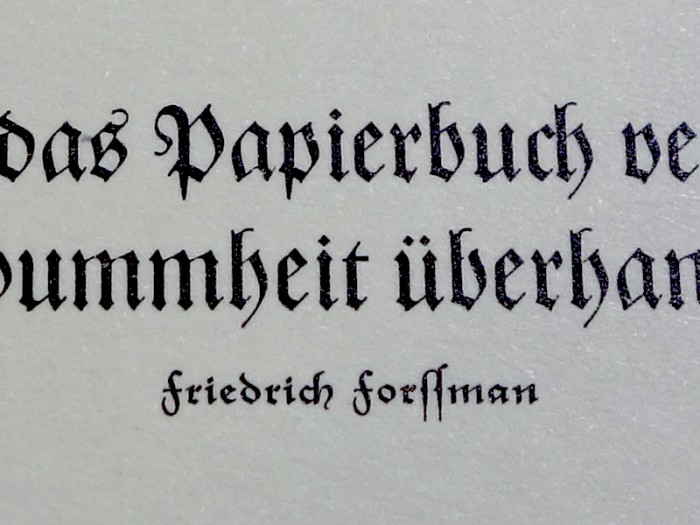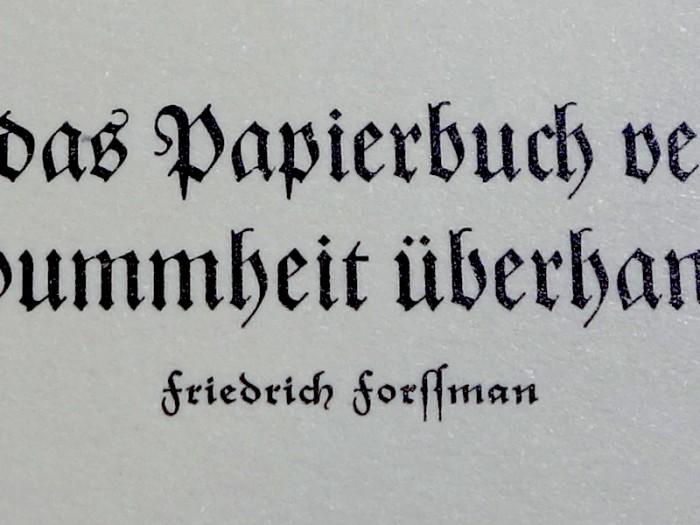
Schriftenkombination
mich würde gerne interessieren, welche Schriftarten beim Kombinieren miteinander gut ausschauen und welche man lieber nicht zusammen kombinieren sollte. Würde mich über Eure Ratschläge und Tipps freuen. lG Katja
Und hui – da hast Du Dir so ziemlich die größte Frage ausgesucht, die man sich im typografischen Bereich stellen kann! Das ist so ähnlich wie: Welche Lebensmittel kann ich kombinieren, um ein tolles Abendessen zu kochen und welche schmecken eher nicht zusammen? ;-)
Ganz wichtig bei so einem Thema ist: Was willst Du mit den Schriften machen? Neben der Tatsache, dass Schriften zum Lesen da sind, sind sie eben auch ein Gestaltungsmittel, mit dem Du viele erdenkliche visuelle Stimmungen und Wirkungen erzielen kannst. Je sachlicher und wissenschaftlicher der Zweck, desto dezenter sollten sich die verwendeten Schriften dem Lesezweck unterordnen. Dazu haben wir hier im Forum gerade eine neue Schriftenliste erstellt, die Schriftenpaarungen für wissenschaftliche Arbeiten vorschlägt.
Geht es hingegen um einen weniger formellen Zweck, dann kann man spielerischer mit den Schriften umgehen und ihnen mehr dekorativen Raum geben. Eine schöne Website, um sich in dieser Richtung von gelungenen Schriftanwendungen inspirieren zu lassen ist »Fonts in use«.
Und ein Klassiker in Sachen Schriftenkombination ist die Tabelle von U&Ic, wobei manch einer die ein oder andere vorgeschlagene Kombination inzwischen als veraltet ansehen wird. Um das grundlegenden Prinzip der Schriftenkombination zu verstehen, finde ich die Liste aber nach wie vor eine gute Idee. Mir ist bloß leider entfallen, wo im Netz diese Übersicht zu finden ist – weiß einer der Kollegen zufällig Rat?  :-?
Nachtrag: Ich habe die Liste gerade selber wiedergefunden!
Bei der klassischen Mischung von Sans mit Serif wirkt es oft harmonisch, wenn den beiden Partnern das gleiche Formenprinzip zugrunde liegt. Auch viele Schriftsippen basieren auf diesem Prinzip.
Beispiele für ein statisches Skelett (abgeleitet von der klassizistischen Antiqua):
• Univers mit Century
• Helvetica mit Walbaum
• Corporate S mit Corporate A
• Tablet Gothic mit Abril
• FF Good mit FF More
Beispiele für ein dynamisches Skelett (abgeleitet von der Renaissance-Antiqua):
• Myriad mit Minion
• Syntax mit Garamond
• FF Quadraat Sans mit FF Quadraat
• FF Milo mit FF Milo Serif
aber auch zwei aus unterschiedlichen gruppen sollte man nicht unbedingt miteinander kombinieren
Kommt drauf an. Eine klassizistische mit einer Renaissance-Schrift geht nicht, aber eine klassizistische mit einer Fraktur geht gut, auch eine Fraktur mit einer Grotesk kann funktionieren, je nachdem welche aber auch fürchterlich schiefgehen.
Ohne etwas historische Schriftkenntnis auf Anwenderseite wird man sowieso entweder nur mit sehr starren Empfehlungen zu guten Ergebnissen kommen, die dann aber kaum mehr praktikabel sind (Du kannst die Lutherfraktur mit der Walbaum mischen, aber eher nicht mit der Museo) oder aber praktikable, weiter gefaßte Empfehlungen kaum verstehen und richtig anwenden können.
Ja ja, hinterher kommst Du mit solchen Einschränkungen um die Ecke …  ;-)
Wie sagt man so schön: »Schön von Weitem, aber bei weitem nicht schön.« Bei mancher Gestaltung muss man schon sehr weit weg gehen, damit sie an Ästhetik gewinnt.
Bei mancher Gestaltung muss man schon sehr weit weg gehen, damit sie an Ästhetik gewinnt.
Dann seht sie von weiten zumindest schon mal sehr entfernt aus*.  :party:
Sagen wir immer, wenn man uns zu etwas fragt und wir noch nicht richtig wissen, ob wir es gut finden sollen. ;-)
Schönheit der einzelnen Schriften reicht nicht für eine gute Schriftmischung. Die beiden hier, die Zentenar und die Rhapsodie, würden in gleicher Größe wohl wehtun. Ebenso kann ein riesiges Didot-Initial in einem Garamond-Text stimmen, während die beiden in gleicher Größe sich kaum vertrügen. Mit Raum, Größe und Farbe kann man vieles zusammenbekommen.
(Die Abbildungen zeigen nur Abzüge von Bleisatz und Holzlettern, keine fertige Drucksache.)